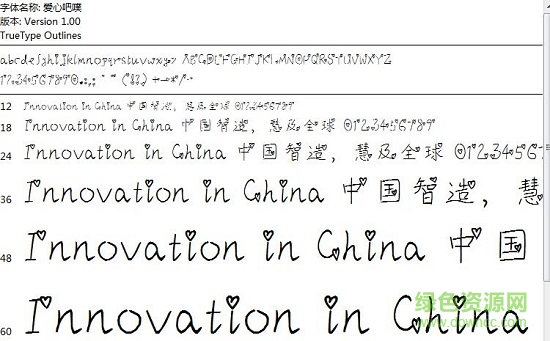
愛(ài)心吧噗ttf是一款非常可愛(ài)的電腦字體,這款字最大的特色就是一眼望去每個(gè)字都帶有愛(ài)心,適合用來(lái)作為主題字體使用,感興趣歡迎下載!
愛(ài)心吧噗字體是一款每個(gè)字都帶有愛(ài)心的可愛(ài)字體,這款字體專為女生設(shè)計(jì)打造,濃郁的手寫風(fēng)格加上每個(gè)字獨(dú)特的愛(ài)心,為你帶來(lái)不一樣的視覺(jué)欣賞體驗(yàn)!